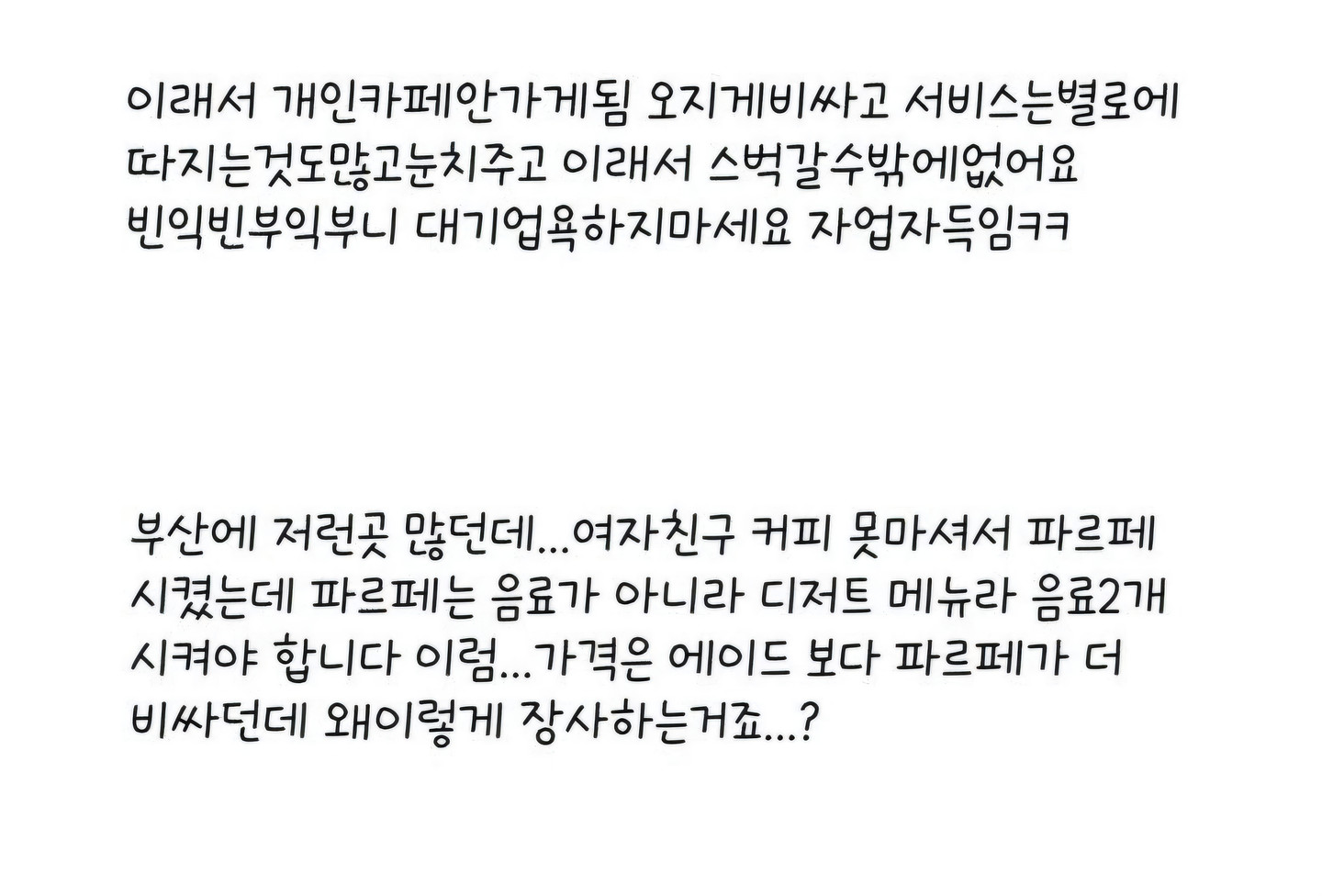
a큐브G
매직으로 쓴 글씨처럼 보입니다. 모음 '기', '리' 등의 획 끝부분이 자연스럽게 삐쳐 올라가거나 꺾이는 독특한 형태를 지니고 있습니다.
a큐브G
매직으로 쓴 글씨처럼 보입니다. 모음 '기', '리' 등의 획 끝부분이 자연스럽게 삐쳐 올라가거나 꺾이는 독특한 형태를 지니고 있습니다.